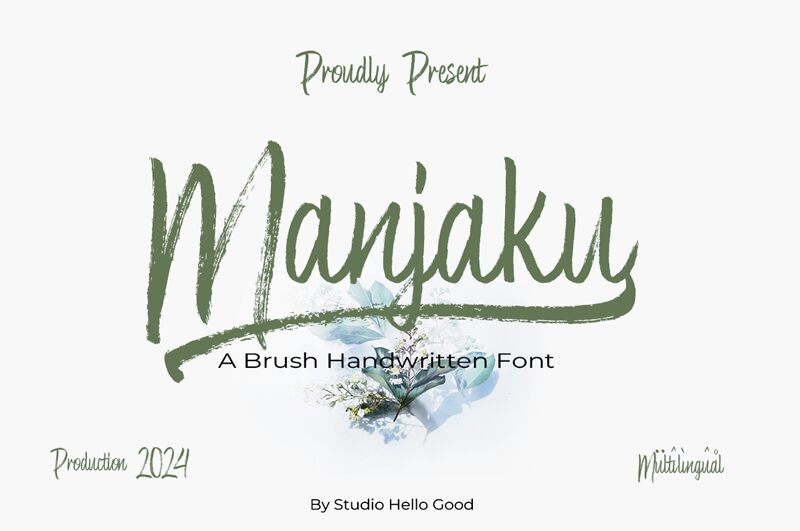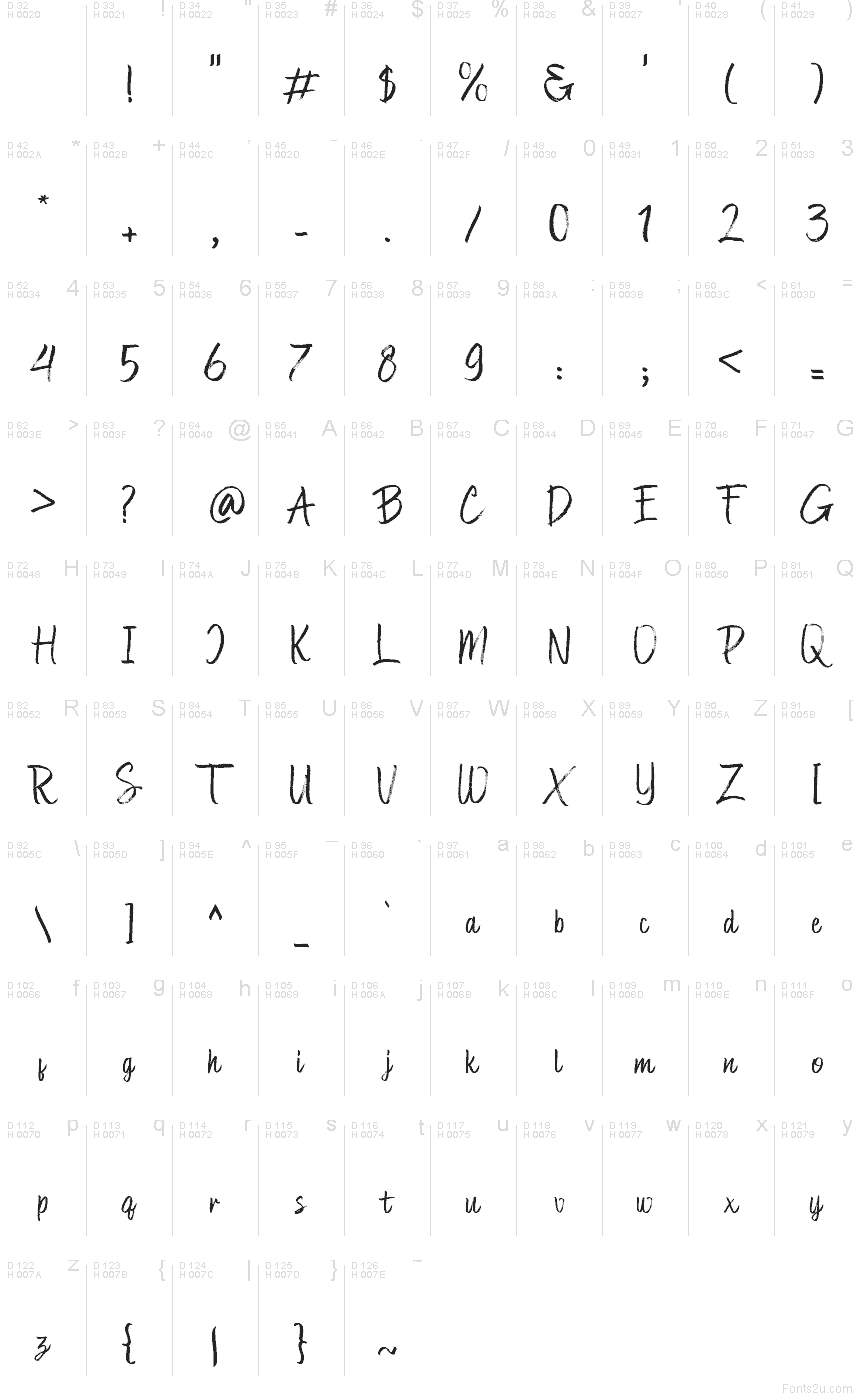
Manjaku
Manjaku, créée par le Studio Hello Good, est une police manuscrite gratuite aux traits bruts façon pinceau, dotée d'un rythme délié et incliné. Ses lettres connectées semblent dessinées spontanément, avec des bords irréguliers et un fini décontracté qui évite un aspect trop soigné.
Manjaku est idéale pour les logos, les visuels de citations, le packaging, les posts sur les réseaux sociaux, les cartons d'invitation et les titres d'affiches, car sa texture dessinée à la main donne aux textes courts un aspect personnel et authentique. Elle est particulièrement efficace si vous recherchez une police script informelle et expressive sans pour autant paraître chargée ou complexe.